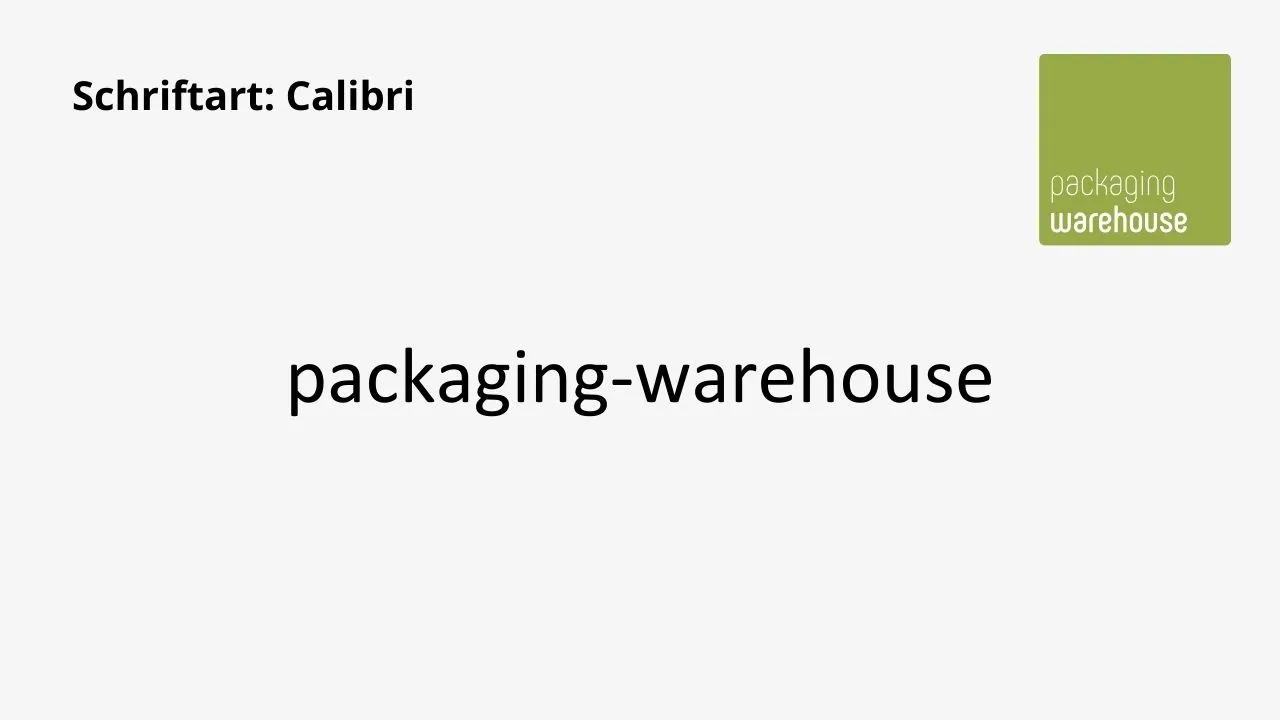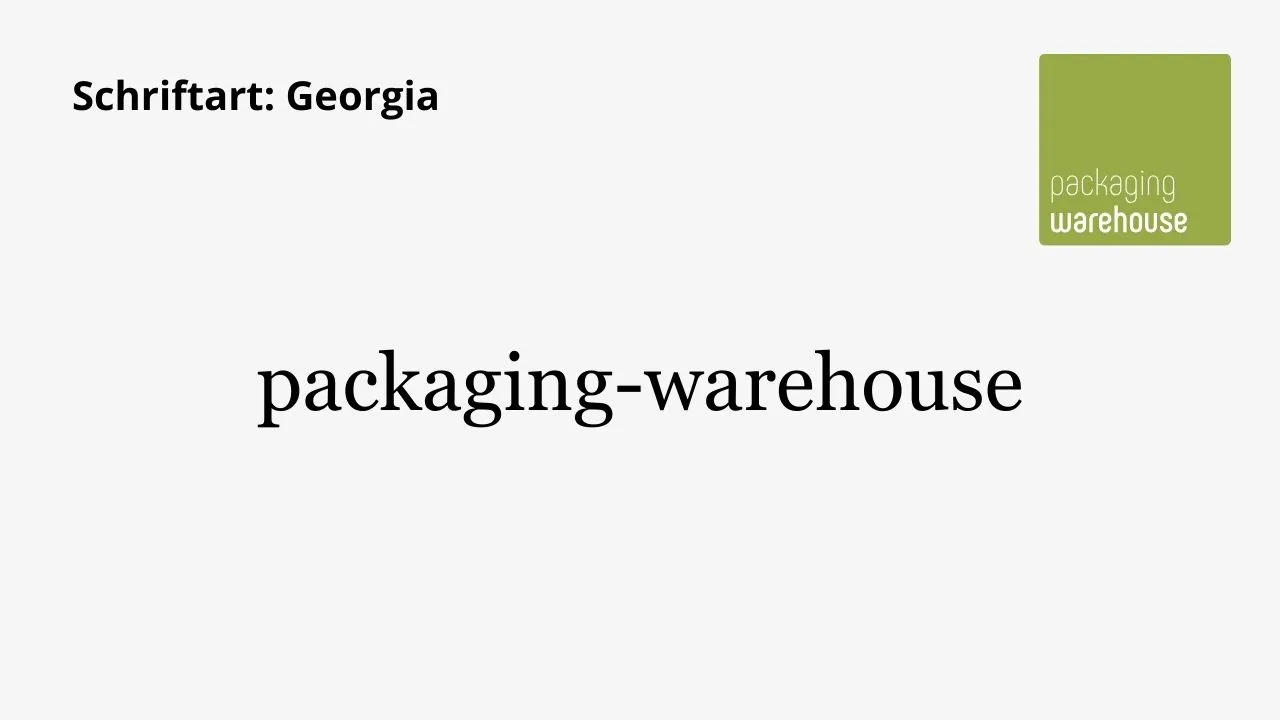
Schriftarten im Design: Vielfalt, Einfluss und Gestaltungsmöglichkeiten
Es ist von entscheidender Bedeutung, die richtige Schriftart für Produkte wie Etiketten und Faltschachteln zu wählen, um die Aufmerksamkeit der Kunden im Laden zu steigern. Die Typografie hat eine faszinierende Geschichte, die mit der Entwicklung menschlicher Schrift beginnt. In der Antike entstanden erste Schriftsysteme, während der Buchdruck im 15. Jahrhundert durch Johannes Gutenberg eine Revolution auslöste. Die Industrialisierung brachte weitere Fortschritte, und heute erleben wir eine Ära digitaler Typografie, in der Schriftarten mithilfe von Computern gestaltet werden. Dieser Wandel von handgeschriebenen Texten über den Buchdruck bis zur digitalen Ära spiegelt technologische Fortschritte und kreative Entwicklungen wider, die unsere Kommunikation und visuelle Darstellung maßgeblich geprägt haben.
Schriftarten sind ein zentraler Bestandteil jedes Designs und haben die Macht, Emotionen zu wecken, Informationen zu vermitteln und die Ästhetik eines Produkts oder einer Botschaft zu beeinflussen. Egal, ob es sich um gedruckte Medien, Websites, Logos oder Produkte handelt, die Auswahl der richtigen Schriftart ist entscheidend für den Erfolg des Designs. Die Art der gewählten Schrift kann die Wahrnehmung des Produkts stark beeinflussen und dabei helfen, die Markenidentität zu stärken oder eine bestimmte Botschaft zu kommunizieren. In diesem Beitrag werden wir die Vielfalt der Schriftarten erkunden, ihre Auswirkungen im Design diskutieren und einige der beliebtesten Schriftarten vorstellen
Lesbarkeit als entscheidender Faktor
Ein entscheidender Aspekt bei der Auswahl einer Schriftart ist die Lesbarkeit. Eine gut lesbare Schrift ist für die Kommunikation von Informationen unerlässlich. Serifenschriften und serifenlose Schriften sind die beiden Hauptkategorien von Schriftarten, die jeweils ihre eigenen Merkmale und Anwendungen haben.
Serifenschriften: Diese Schriftarten sind durch kleine Verzierungen an den Enden der Buchstaben, genannt Serifen, gekennzeichnet. Serifenschriften werden oft als traditionell, elegant und leicht zu lesen angesehen, insbesondere in gedruckten Texten wie Büchern und Zeitungen.
Serifenlose Schriften: Im Gegensatz dazu fehlen serifenlosen Schriften diese Verzierungen an den Buchstabenenden. Sie werden oft als modern, klar und direkt wahrgenommen. Diese Schriftarten eignen sich gut für Bildschirmanwendungen und haben in der digitalen Welt an Bedeutung gewonnen.
Was sind typografische merkmale?
Beliebte Schriftarten und ihre Anwendung
Es gibt unzählige Schriftarten, aber einige haben sich aufgrund ihrer Vielseitigkeit und Ästhetik als besonders beliebt erwiesen. Hier sind zehn Schriftarten, die in verschiedenen Designs häufig Verwendung finden:
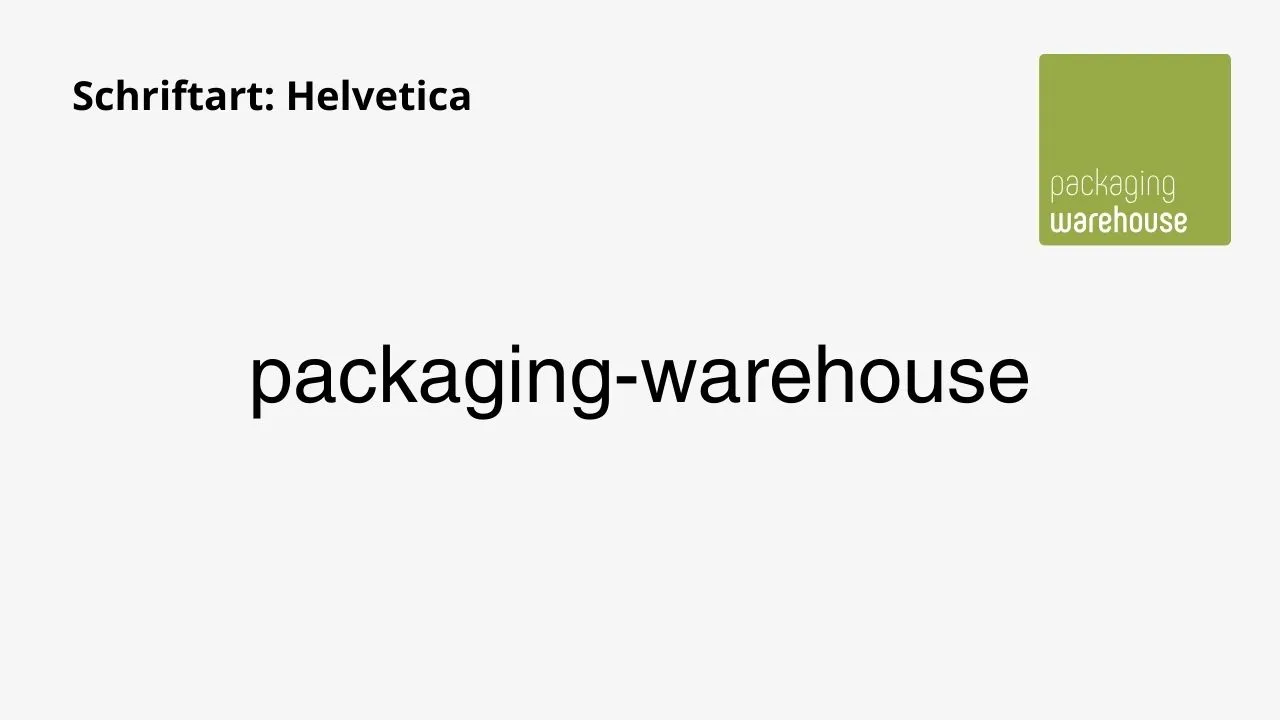
Helvetica
Helvetica ist eine populäre serifenlose Schrift, 1957 in der Schweiz entworfen. Bekannt für Einfachheit und Vielseitigkeit, ist sie in verschiedenen Stilen verfügbar, von Regular bis Bold. Ihr minimalistisches Design und fehlende Serifen verleihen ihr Modernität und Lesbarkeit. Die Schrift wird häufig für diverse Designs verwendet, von Printmedien bis zu digitalen Anwendungen. Marken wie BMW nutzen Helvetica für ein professionelles und zeitgemäßes Image. Ihr klarer Stil hat sie zu einer zeitlosen Schrift gemacht, die auch heute noch weit verbreitet und beliebt ist.
Times New Roman
Times New Roman ist eine klassische Serifenschrift, die erstmals 1932 veröffentlicht wurde. Sie ist bekannt für ihre Lesbarkeit in gedruckten Texten und wird oft in Büchern, Zeitungen und akademischen Arbeiten verwendet. Ihre Serifen verleihen ihr ein traditionelles und elegantes Erscheinungsbild. Die Schrift ist aufgrund ihrer Geschichte und Vertrautheit beliebt, obwohl sie in digitalen Anwendungen nicht immer die erste Wahl ist.
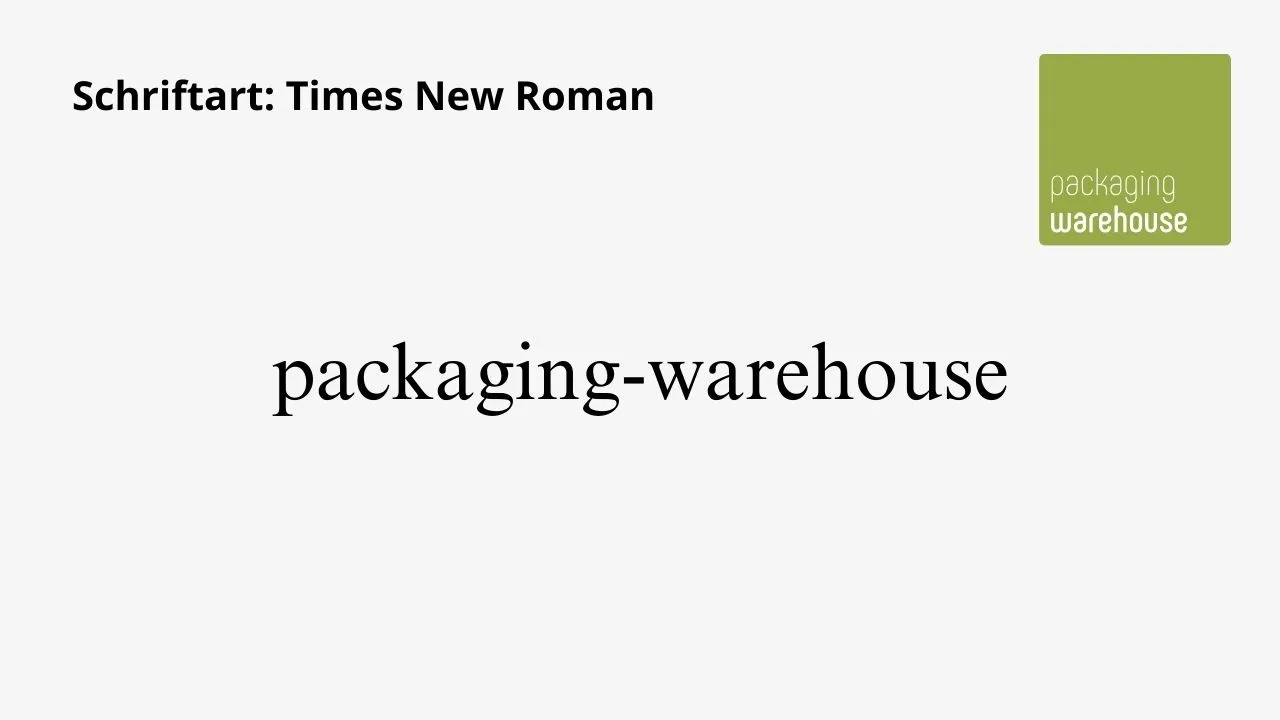
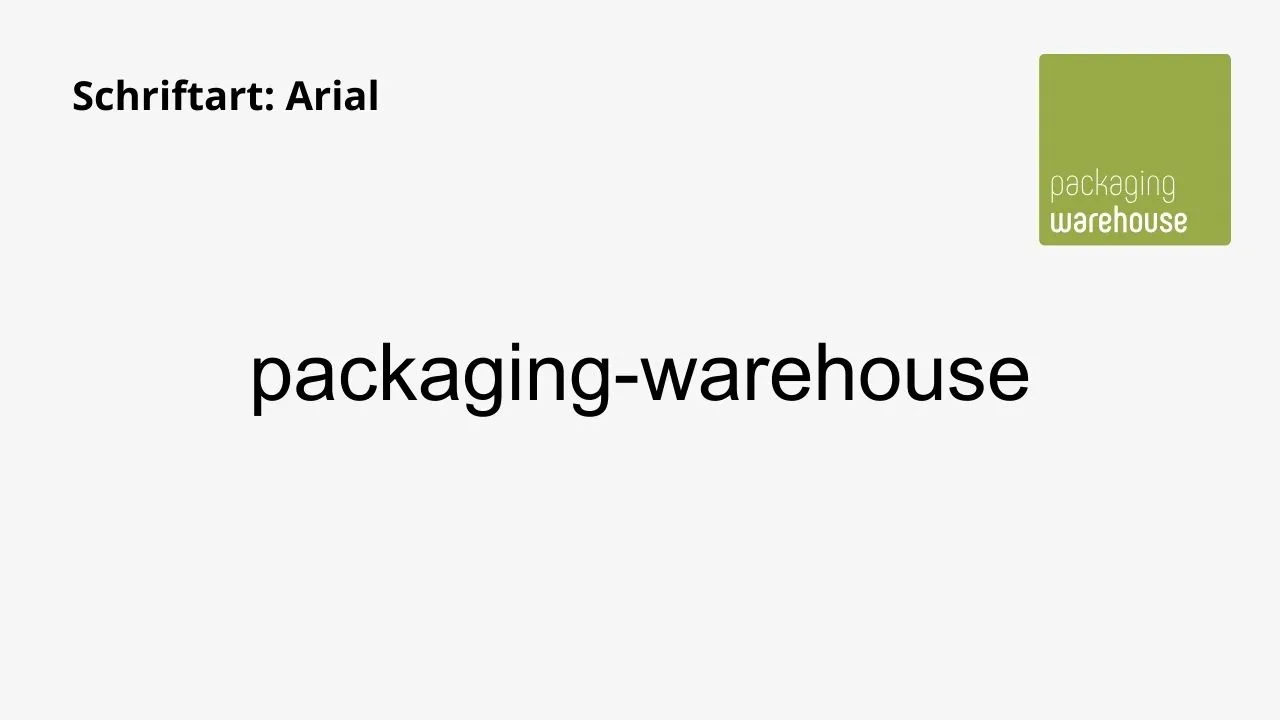
Arial
Arial ist eine serifenlose Schrift, die der Helvetica ähnelt und für ihre Lesbarkeit auf Bildschirmen geschätzt wird. Sie wurde 1982 von Monotype entworfen und ist in verschiedenen Gewichten verfügbar. Arial wird häufig für digitale Anwendungen wie Websites, Präsentationen und Anzeigen verwendet. Ihre klaren Linien und einfaches Design machen sie gut lesbar und vielseitig einsetzbar.
Verdana
Verdana ist eine weitere serifenlose Schrift, die speziell für die Anzeige auf Bildschirmen entwickelt wurde. Sie wurde von Matthew Carter für Microsoft entworfen und ist für ihre Lesbarkeit in kleinen Größen bekannt. Verdana zeichnet sich durch klare Buchstaben und großzügige Buchstabenspatien aus, was sie ideal für Online-Texte macht, besonders wenn eine gute Lesbarkeit auf verschiedenen Bildschirmgrößen erforderlich ist.
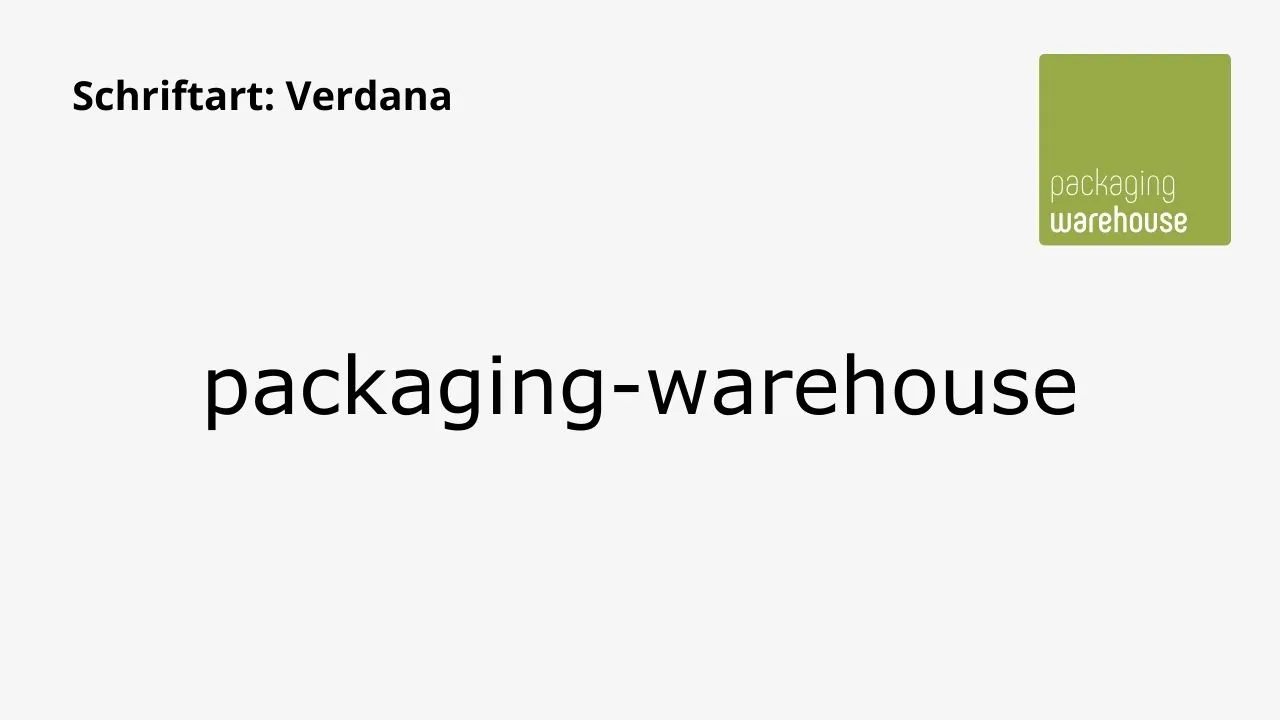
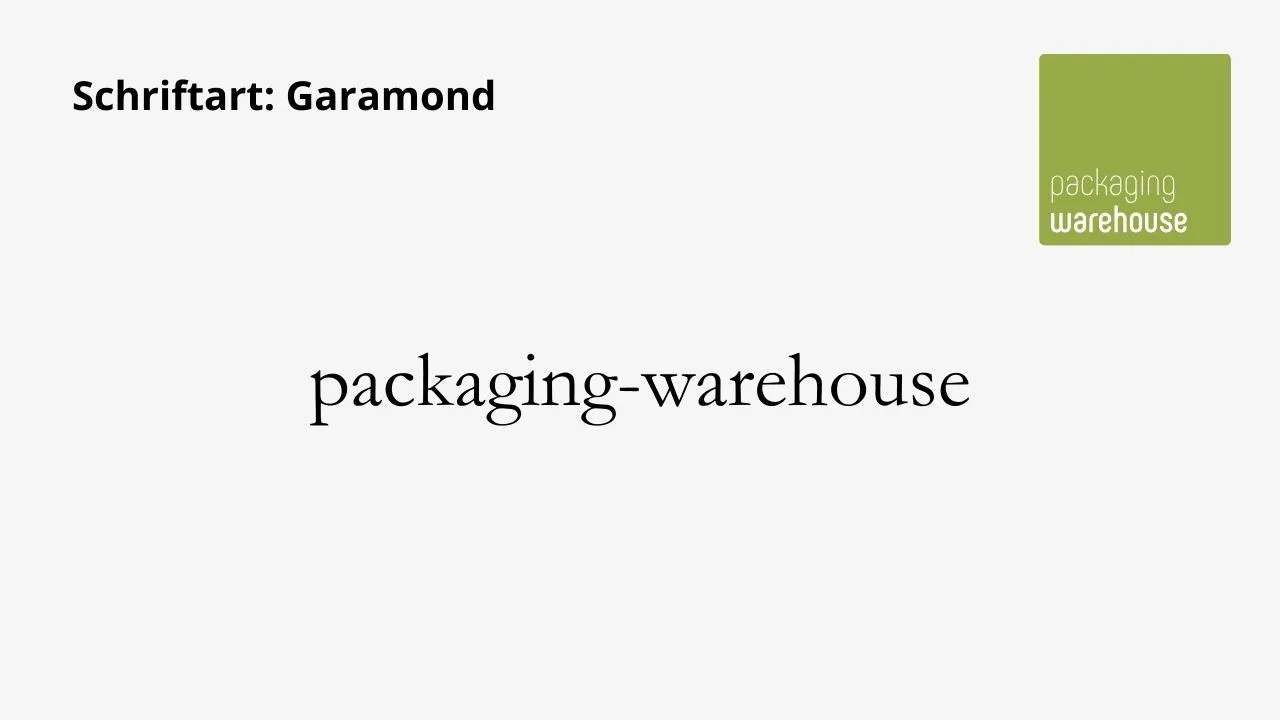
Garamond
Garamond ist eine elegante Serifenschrift mit historischem Flair, die auf Entwürfen von Claude Garamond im 16. Jahrhundert basiert. Sie zeichnet sich durch ihre schlanken und gut proportionierten Buchstaben aus. Diese Schrift wird oft in gedruckten Texten wie Büchern und Magazinen für ihren klassischen und anspruchsvollen Stil verwendet.
Futura
Futura ist eine markante serifenlose Schrift, die Modernität und klare Linien verkörpert. Entwickelt von Paul Renner in den 1920er Jahren, ist sie für ihr geometrisches Design bekannt. Futura wird häufig für grafische Designs, Beschilderungen und Logos verwendet, um einen künstlerischen und zeitgemäßen Eindruck zu vermitteln.
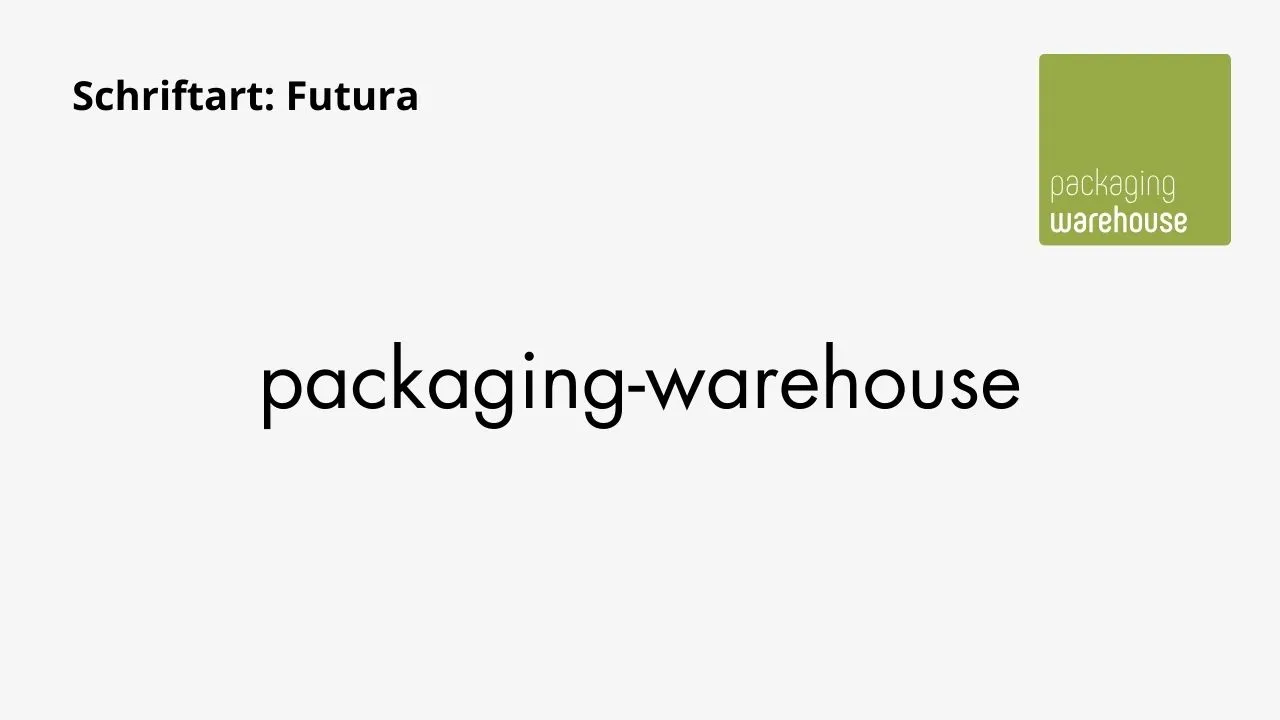
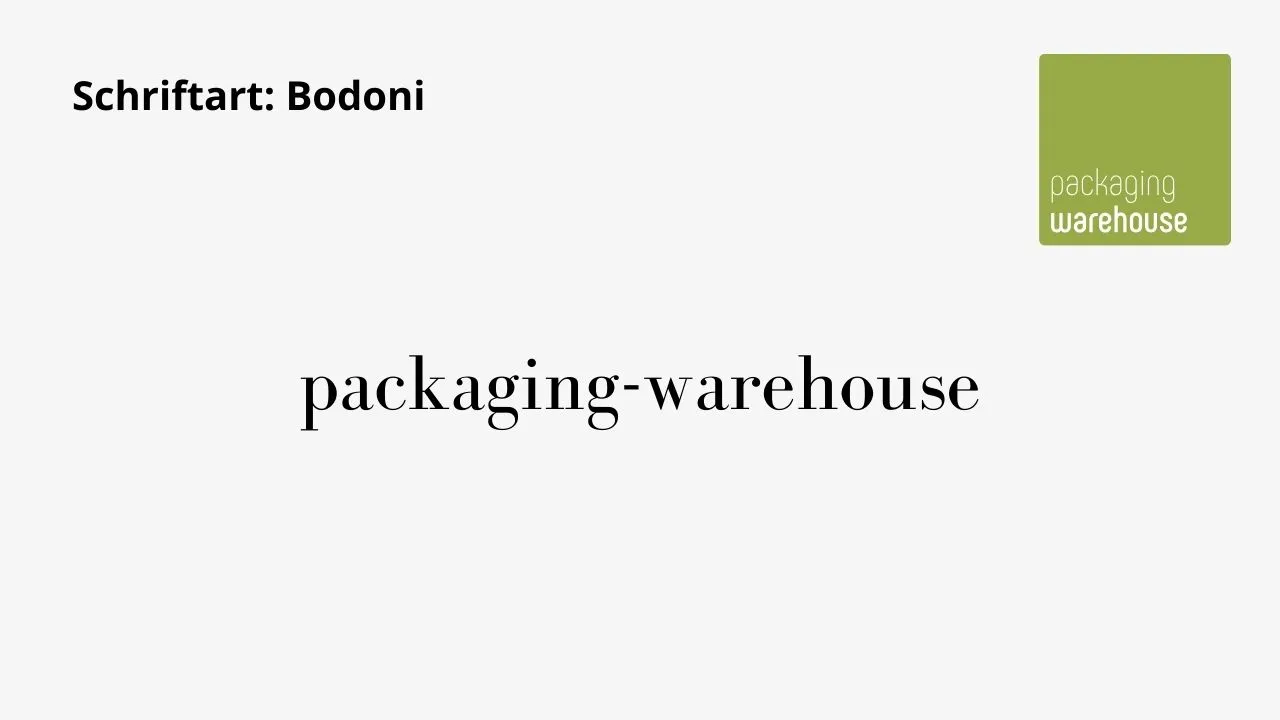
Bodoni
Bodoni ist eine elegante Serifenschrift, bekannt für den starken Kontrast zwischen dünnen und fetten Linien. Entworfen von Giambattista Bodoni im späten 18. Jahrhundert, strahlt sie Raffinesse und Klarheit aus. Bodoni wird oft in Modezeitschriften, Luxusmarken und Werbematerialien verwendet, um eine edle und anspruchsvolle Atmosphäre zu schaffen.
Es ist wichtig zu betonen, dass dies nur eine kleine Auswahl der Möglichkeiten darstellt, wie Schriftarten miteinander interagieren können. Es gibt noch zahlreiche weitere Aspekte zu entdecken! Experimentiere und suche nach einer Kombination, die sowohl visuell ansprechend als auch funktional ist – das ist der Schlüssel zu einer gelungenen Zusammenstellung verschiedener Schriftarten.